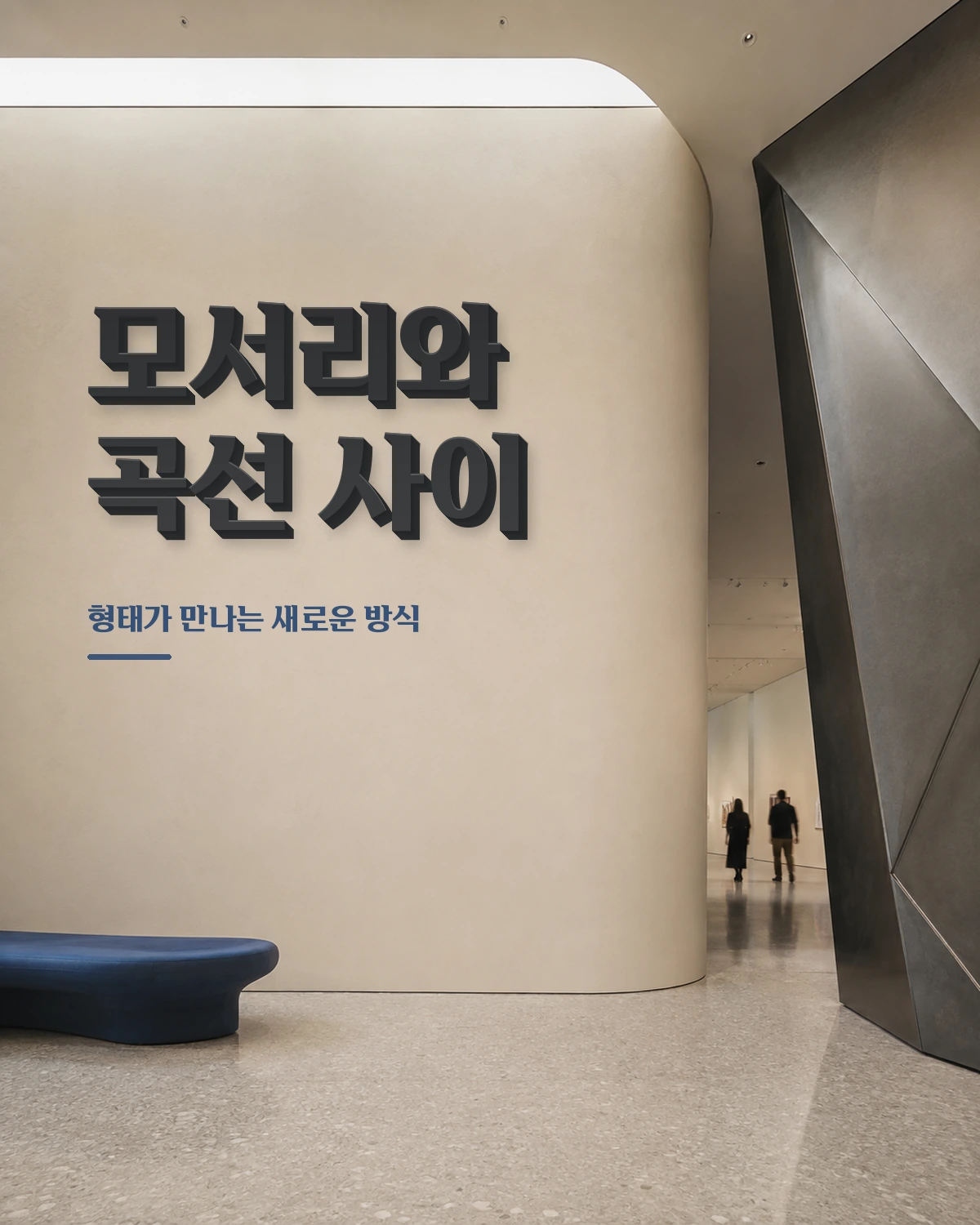
푸라닭 젠틀고딕 — (주)아이더스코리아에서 배포하는 무료 폰트입니다. 각진 꺾임과 둥근 이음이 함께 도는 제목용 고딕
치킨 브랜드 푸라닭을 운영하는 아이더스코리아가 폰트릭스와 함께 만들어 2022년 한글날에 공개한 서체입니다. 브랜드 이념인 치킨, 요리가 되다를 서체로 표현하는 것이 목표였습니다.
모티브가 로고와 심볼 두 곳에서 왔습니다. 제작사 설명 그대로, 로고의 다이아몬드 모양 각진 형태를 모티브로 한 곧고 단단한 골격과 세리프에, 심볼의 닭 형상에서 착안한 부드러운 곡선을 더했습니다. 이름은 고딕이지만 획 끝에 세리프가 붙어 있어서 분류가 갈리는 서체인데, 그 세리프가 고급스러운 인상을 만듭니다. 활용성을 넓히려고 획의 폭 대비를 줄였다는 설명도 붙습니다.
굵기는 하나이고 픽토그램 40종이 함께 들어 있습니다. 메뉴판이나 패키지, 광고 카피처럼 짧고 굵게 읽히는 자리에 맞습니다. 굵기가 하나라 위계를 굵기로 나눌 수 없으니 긴 본문에는 다른 서체를 두세요. 수정과 변경이 허용되고 로고와 마크에도 쓸 수 있는 넓은 라이선스입니다.